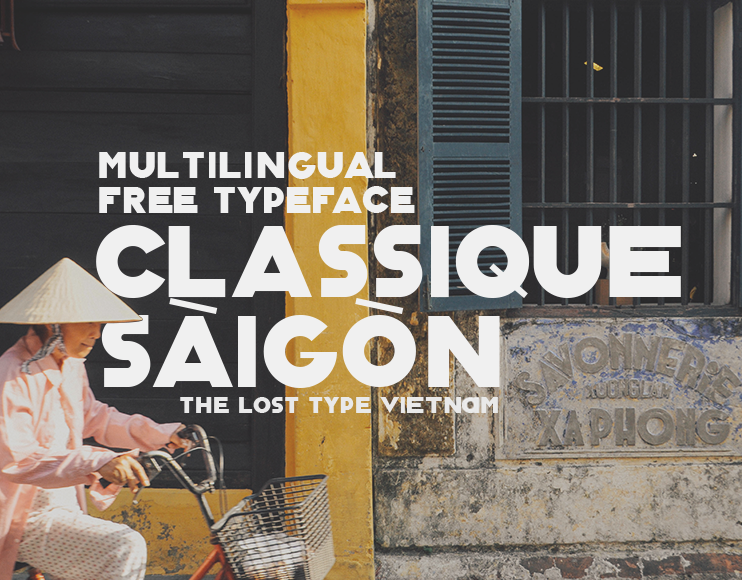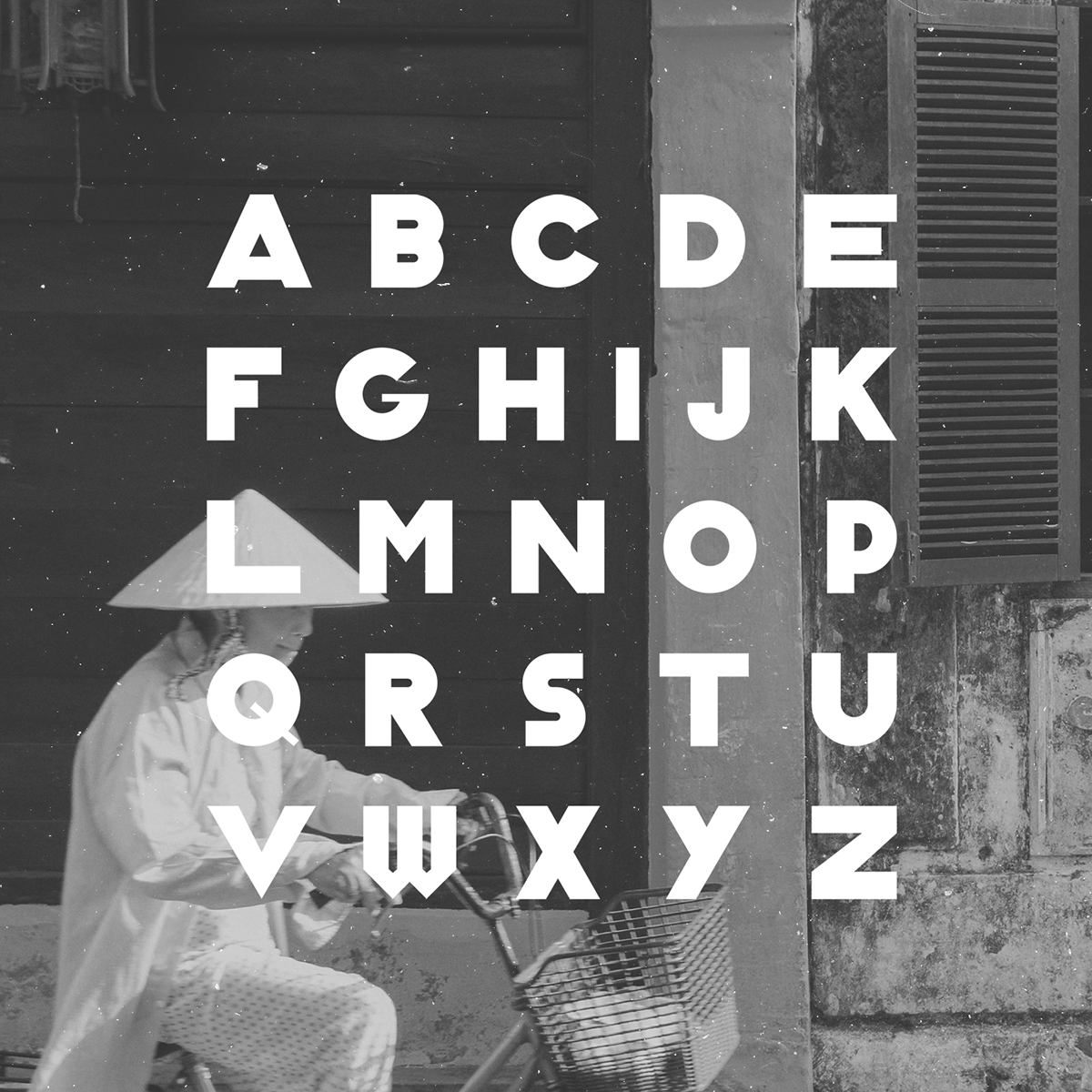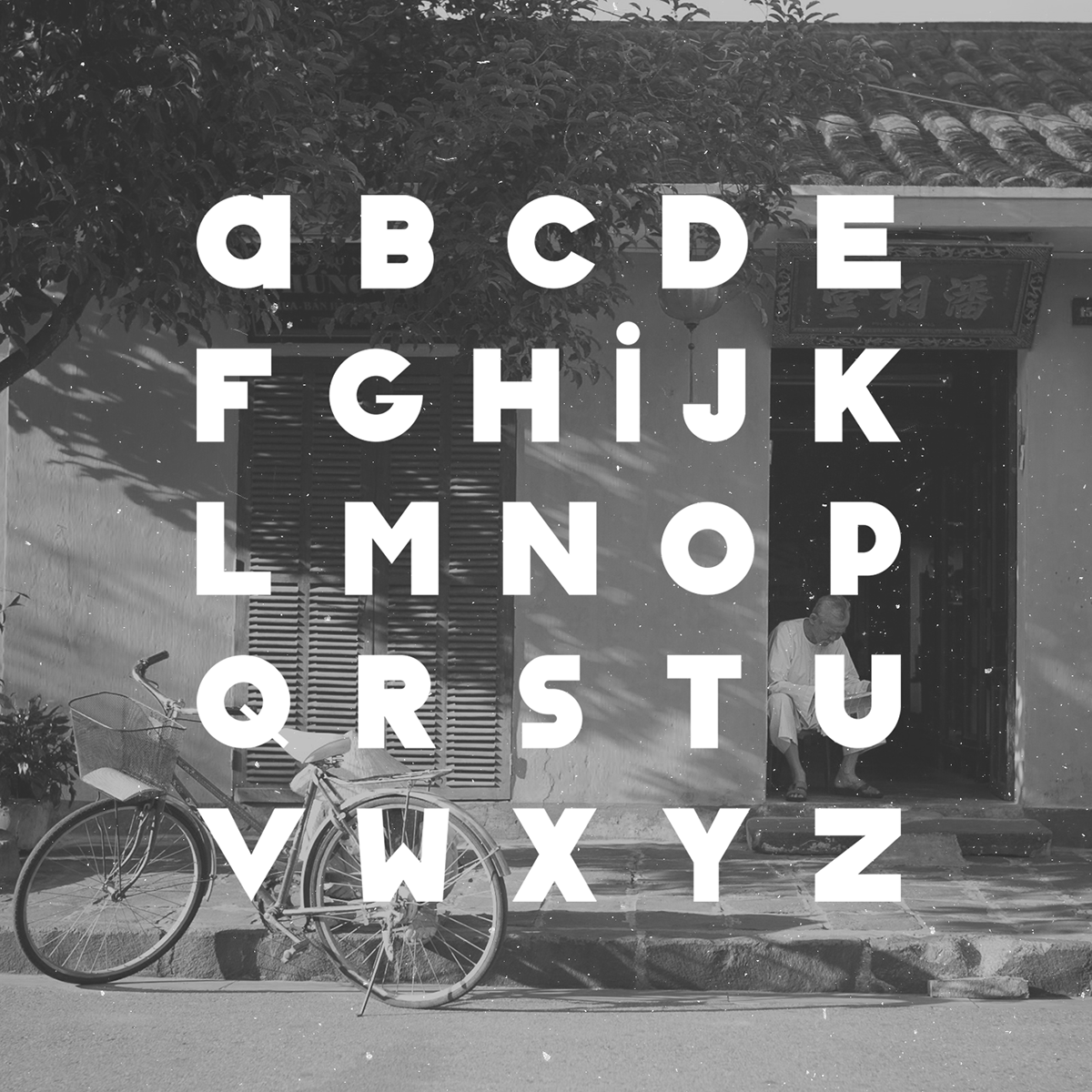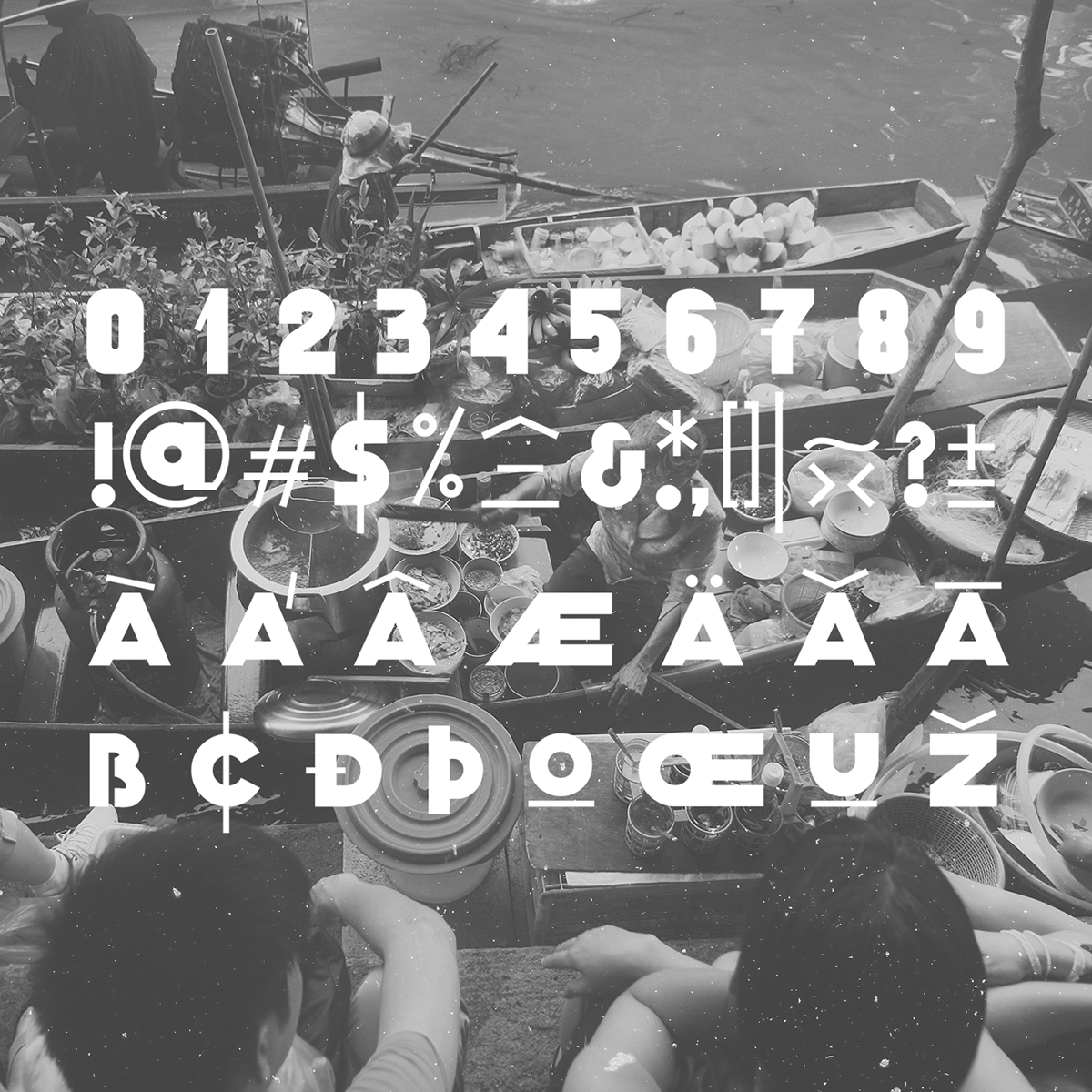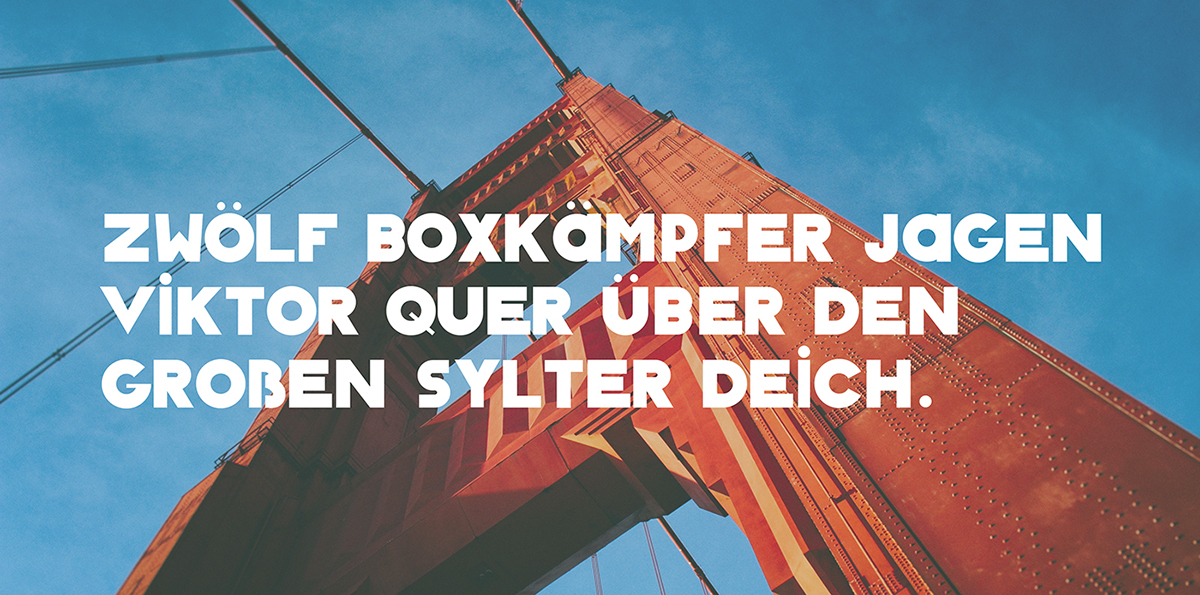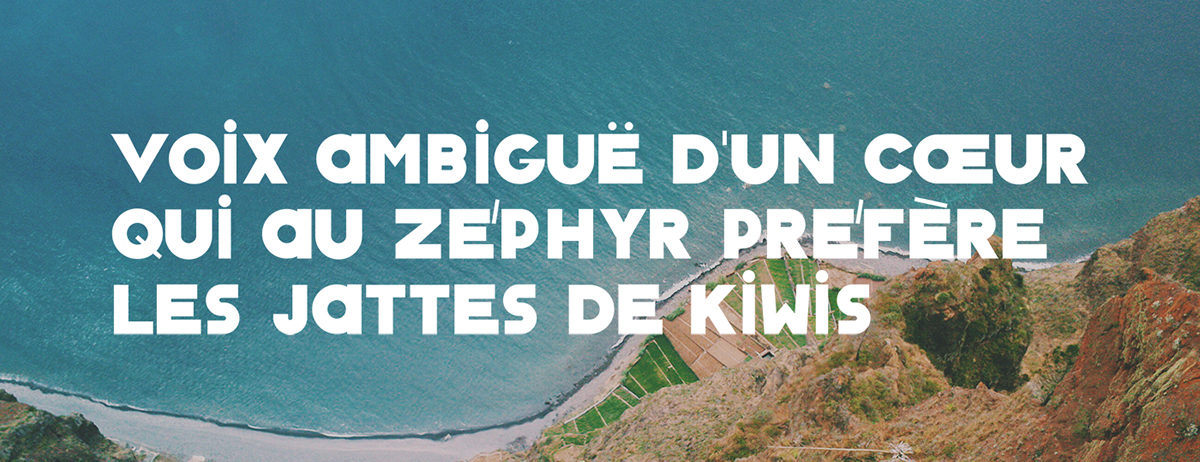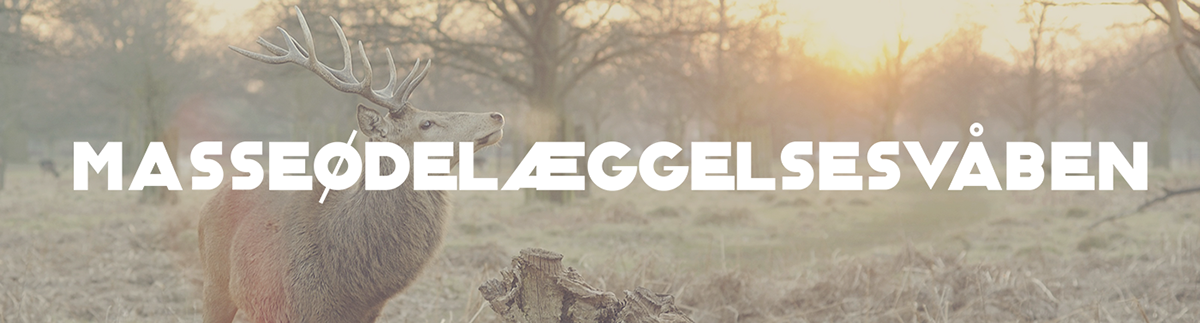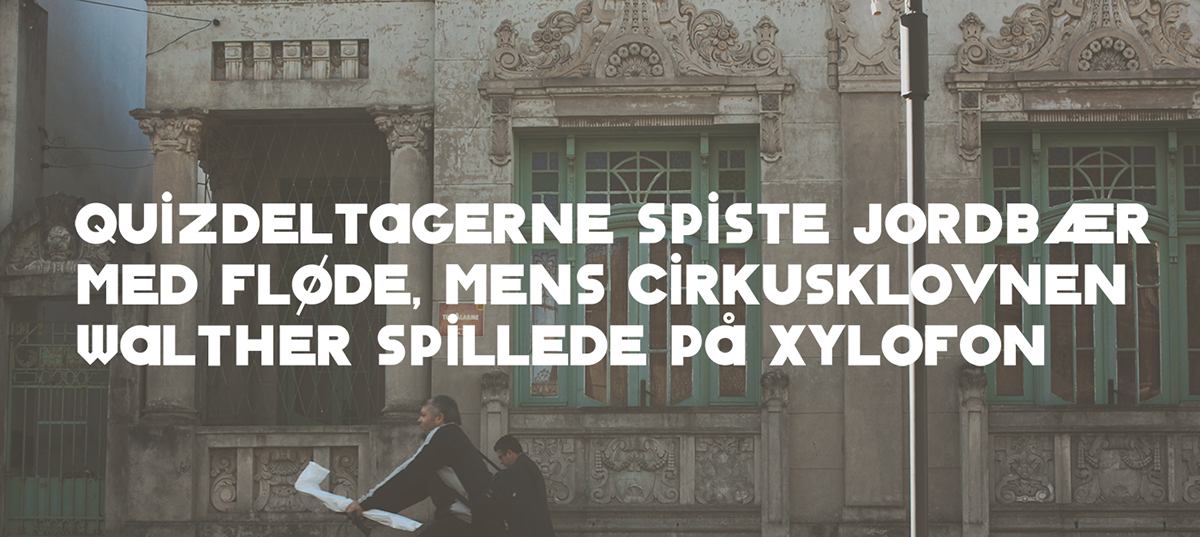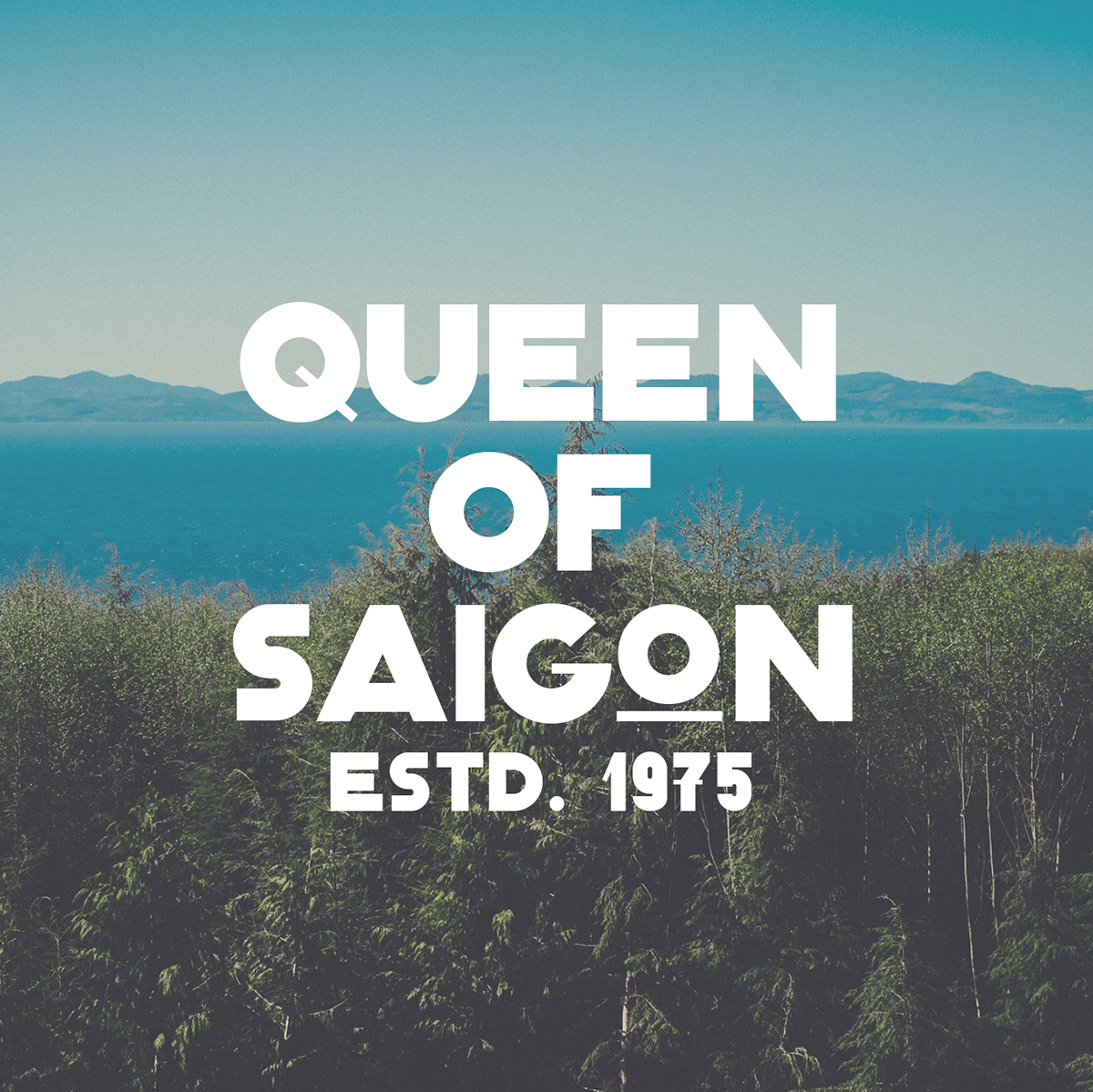
Classique Saigon là một font chữ được thực hiện bởi Manh Nguyen, một designer theo đuổi lĩnh vực sáng tác font chữ ở Hà Nội, Việt Nam. Do đam mê những bảng hiệu quảng cáo và những pa nô thời xưa, nên anh đã quyết định Project này theo phong cách Sài Gòn xưa. Và chính anh cũng được cảm hứng dựa trên Project “Lưu Chữ” (The Lost Type Vietnam – #luuchu), được thực hiện bởi Huy Le, với những bức hình xuyên suốt các bản hiệu với những font chữ kẻ tay ngày xưa còn sót lại trên khắp đất nước để đưa hình ảnh Việt Nam xinh đẹp lan khắp thế giới. Với niềm cảm hứng này, Mạnh đã đưa cảm xúc của anh vào font chữ của mình một cách ấn tượng và đầy xúc cảm – là một Sài Gòn đầy chất nghệ thuật.
Classique Saigon là một font hiển thị mạnh mẽ, đậm, và có thể được sử dụng ở nhiều ngôn ngữ khác nhau, được cảm hứng bởi font chữ viết tay Retro nhưng cũng có nét hiện đại riêng. Và được chia sẻ miễn phí cho mọi người. Nào, hãy cùng lướt qua và chia sẻ font chữ tuyệt vời này đến các bạn bè của mình nhé!